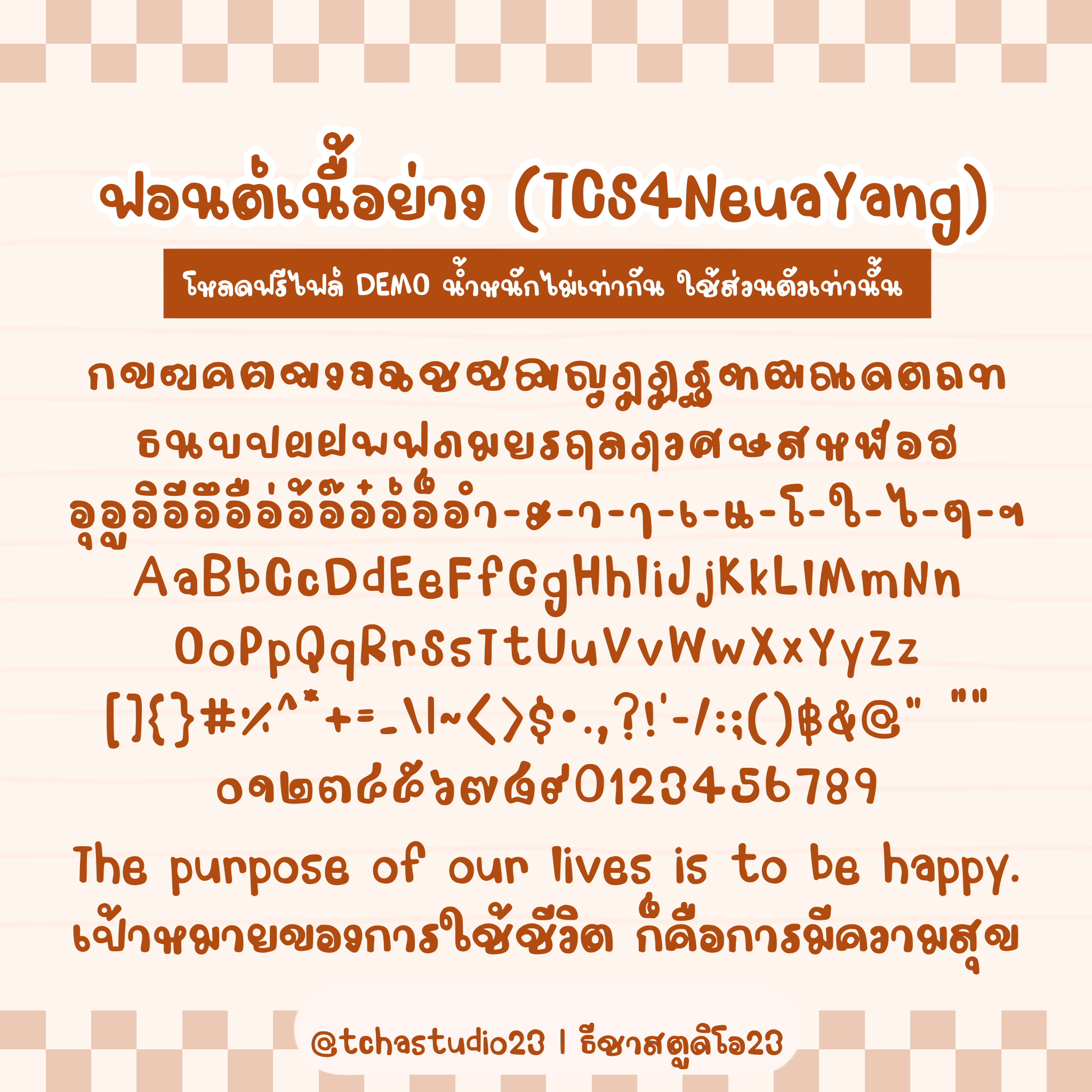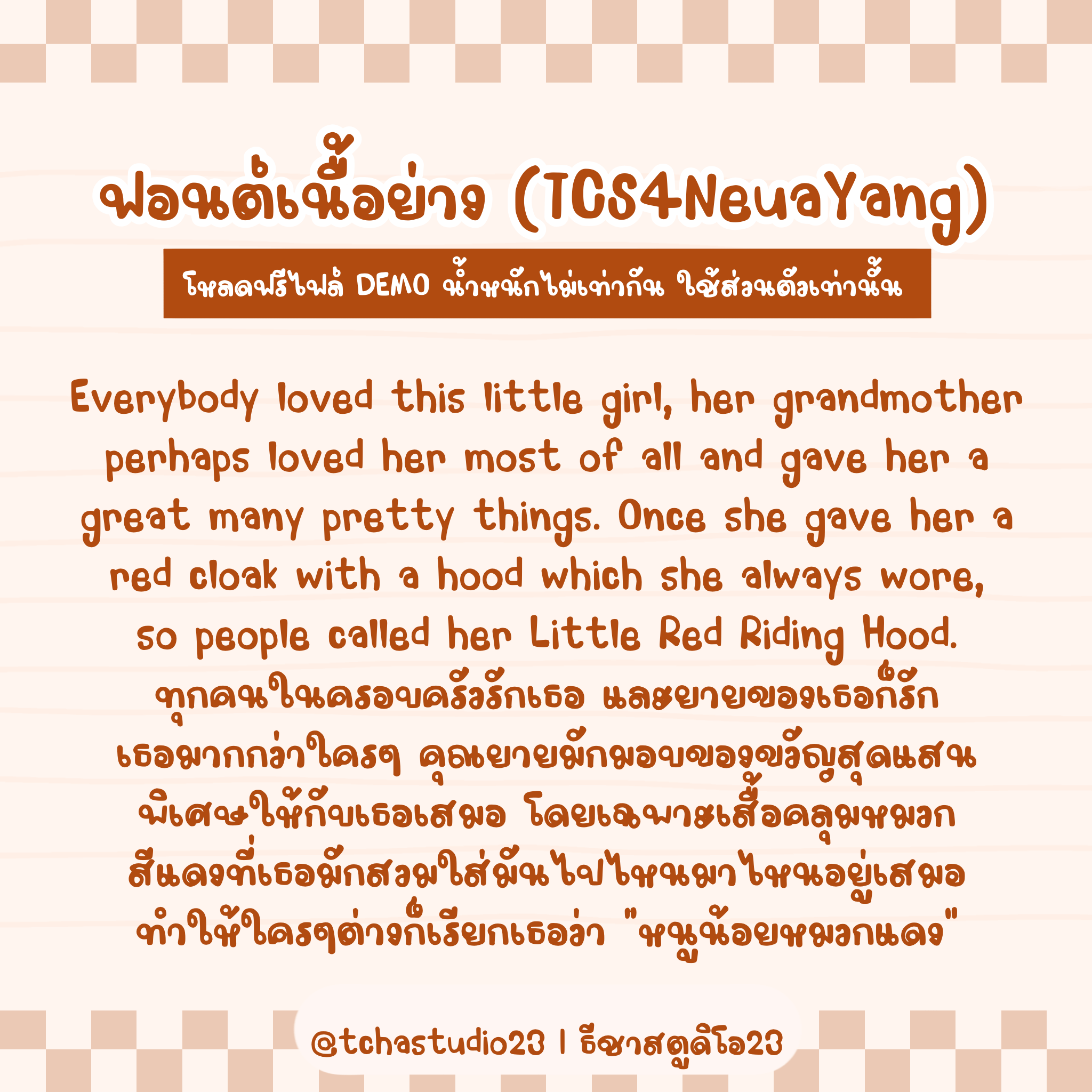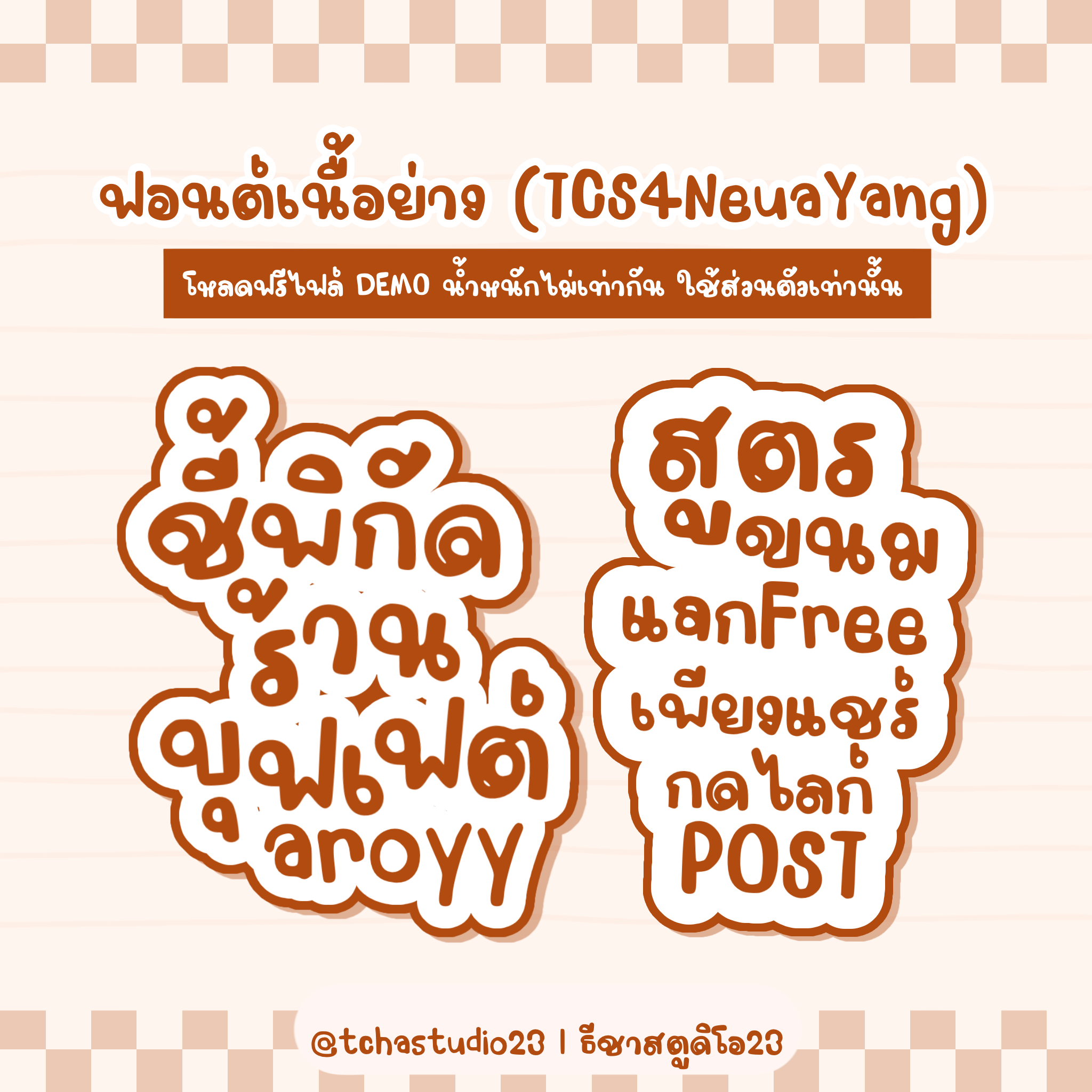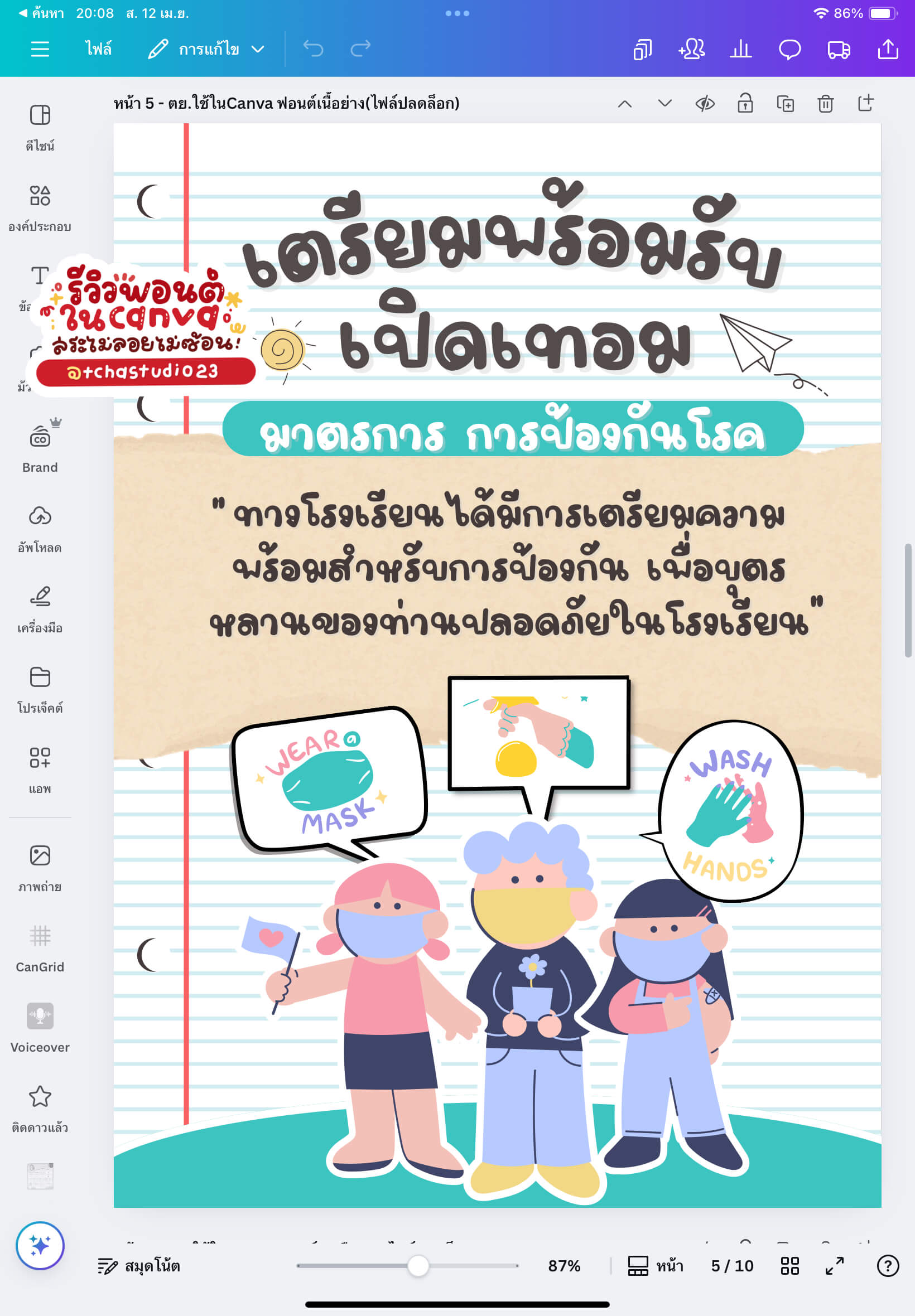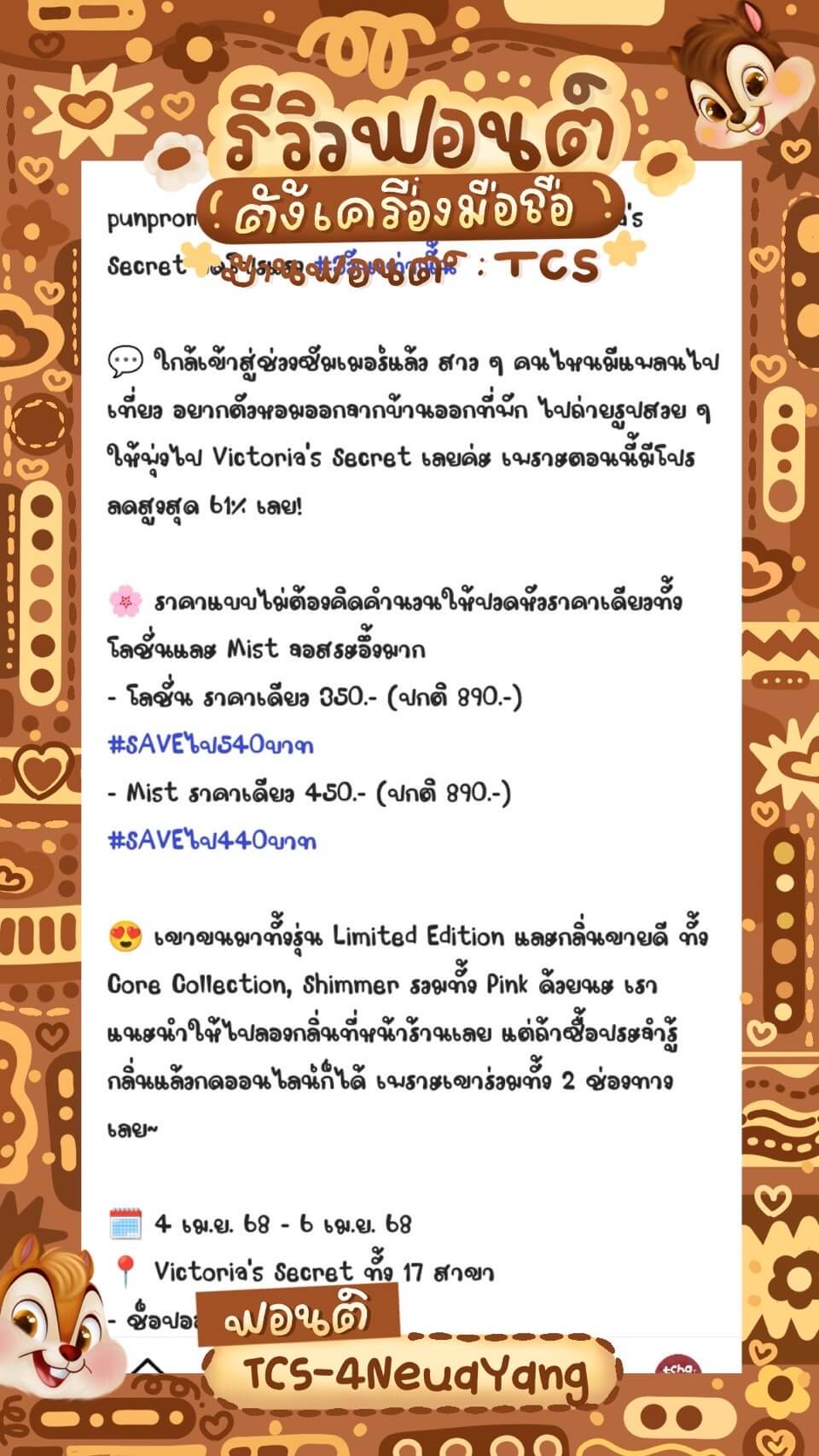
เนื้อย่าง (TCS4NeuaYang)
ฟอนต์เนื้อย่าง (TCS4NeuaYang) เป็นฟอนต์ที่ลงน้ำหนักเส้นไม่เท่ากัน
– ไฟล์เวอร์ชันทดลอง (Demo) ยังไม่ปรับสระ มีน้ำหนักไม่เท่ากัน